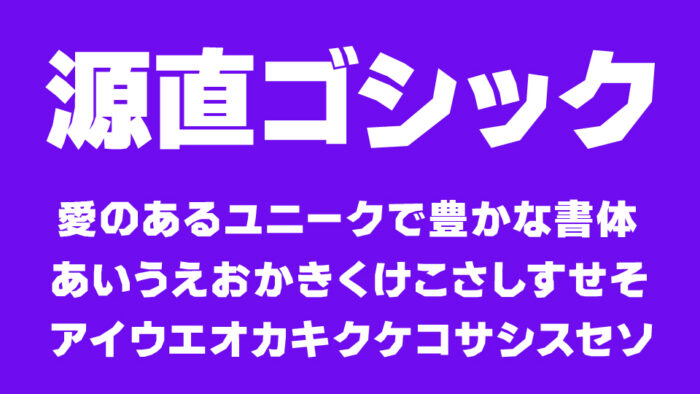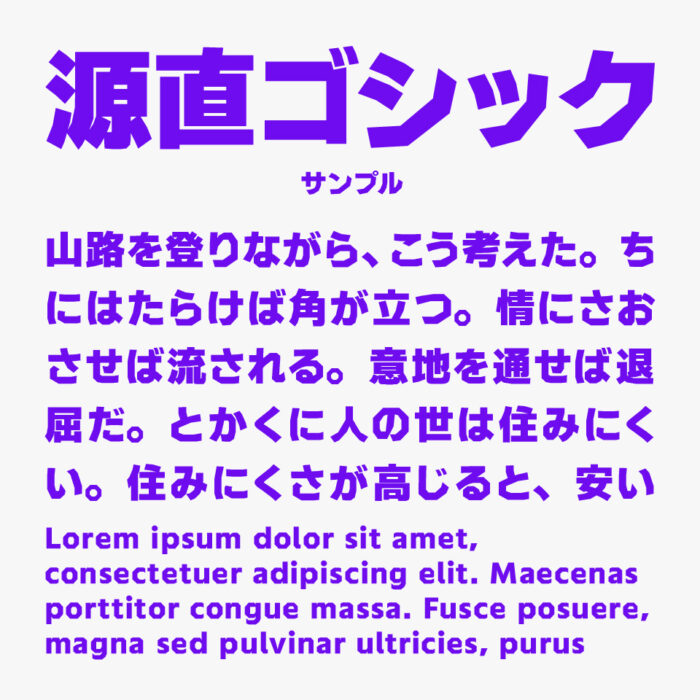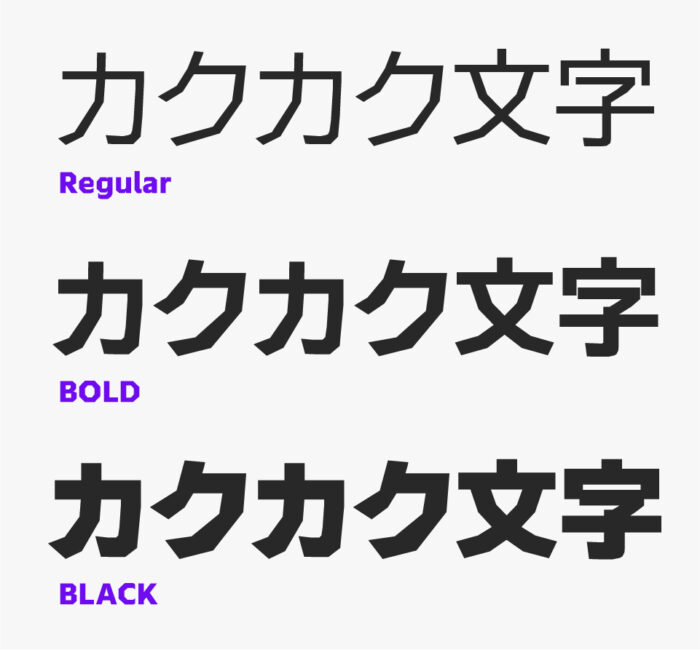
源直ゴシック
源直ゴシックフォントは、「源暎エムゴ」「源暎モノゴ」フォントをベースに直線で再構成された角張ったフォルムがユニークなゴシック体フォントです。
明快で力強い直線的に作られているので、一般的なゴシックよりカクカクした骨格がとっても個性的で面白みのあるゴシック体となっています。
源直ゴシック EMG(全5ウェイト)、源直ゴシック MNG (全2ウェイト)とバリエーションがあり、複数のウェイト展開も用意されています。場面に応じて使い分けることができるので便利ですね。